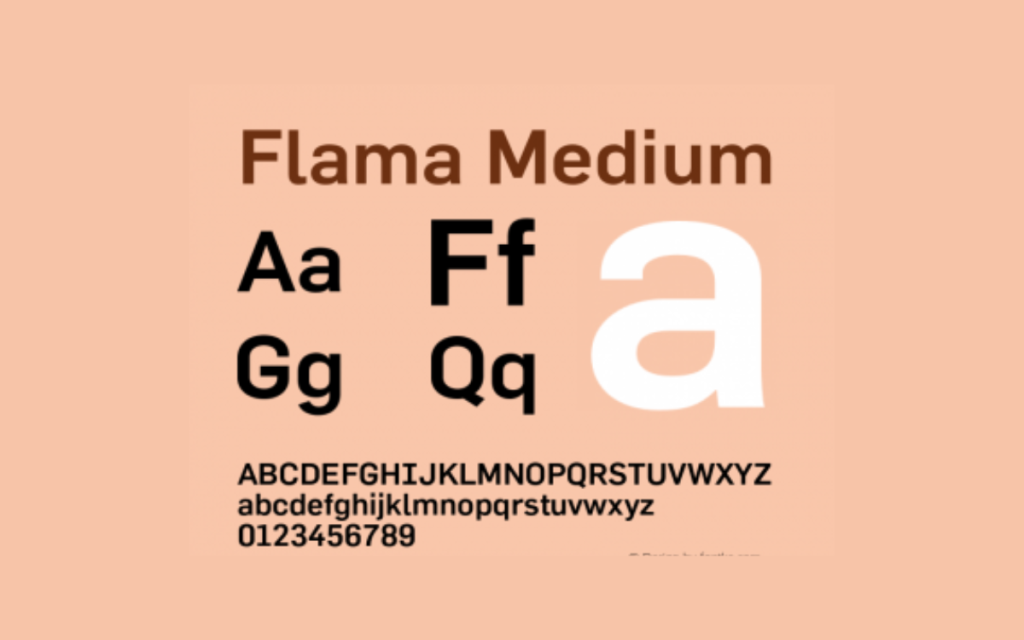
Tác giả: Mario Feliciano
Ngày phát hành: 2006
Phân loại: Cá tính
Font Flama là một trong những kiểu chữ hiện đại được thiết kế với sự tinh tế và linh hoạt, phù hợp cho nhiều mục đích sử dụng. Được yêu thích bởi sự rõ ràng và tính thẩm mỹ cao, Font Flama là font chữ thuộc bộ font chữ không chân không chỉ giúp cải thiện trải nghiệm người dùng mà còn tạo nên sự chuyên nghiệp cho các sản phẩm thiết kế đồ họa. Với đặc tính dễ đọc và tính ứng dụng cao, kiểu chữ này trở thành lựa chọn lý tưởng cho các dự án sáng tạo, từ thiết kế logo, tiêu đề, đến giao diện người dùng và nội dung in ấn.